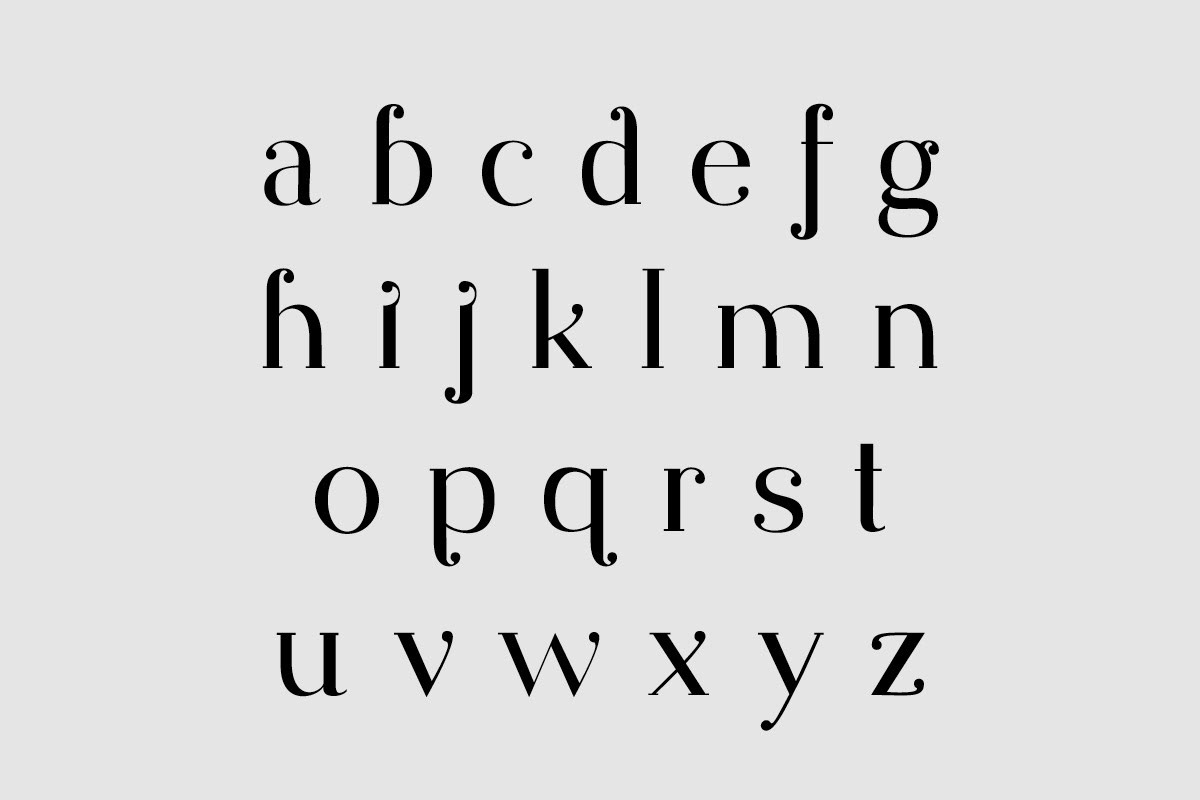
Download Font Chữ Minna Drop là lựa chọn hoàn hảo cho những ai yêu thích kiểu chữ độc đáo, sáng tạo. Minna Drop mang phong cách mềm mại, hiện đại, phù hợp cho các thiết kế thời trang, quảng cáo, và in ấn. Với nét chữ tinh tế, thanh thoát, font này giúp tác phẩm của bạn trở nên nổi bật và cuốn hút hơn. hãy cùng theo dõi Sadesign nhé
1. Giới thiệu về Font chữ Minna Drop .
Minna Drop là một font chữ cho Photoshop tôn lên vẻ đẹp thanh lịch và cổ điển. Đây là font chữ phù hợp để trang trí áp phích và thiệp cổ điển.